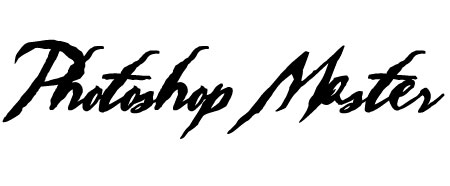
Великолепный Шрифт
Крутой шрифт =)
Mika xD, я видел очень большое сходство с группой (в названии) Daft Punk...искал его)) думал выдернуть ввиде самой картинки. То, что мне нужно. Спасибо;))
То что нужно если ещё пару кисточек с кровью рядом то вобще
А кто нибудь знает,из какого фильма или группы этот шрифт?